之前就有听说过一句话,见字如见人。字写得怎么样,可能也就代表了,这个人怎么样。写字其实也是一件非常重要的事情,在中国的考试中,写字也是占据了很大一部分的分数的。如果你字写得比较工整,可能也会添加一些额外的分数。
但是如果字写得特别的差,回答的比较准确,写得非常的潦草看都看不清楚,老师可能也会扣除一些相应的分数。因此对于中国人来说写一手好字,也是非常重要的。在古代的时候,讲究的是写好毛笔字。随着时代的发展,字也进行了一定的发展。以前都是一些繁体字,慢慢地也就开始简化。
从以前的毛笔字变成了现在的硬笔字,大家不再去练习毛笔书法,开始练习硬笔书法。为了让孩子们能够练好字了,市面上也开始出现了大量的字帖,希望可以让每个人都将自己的字练好。但即使有字帖的发明,大家所写的字也都各有不同。
并且随着网络的发达,有一些人就特别喜欢自创一些字体,发在网络上。在这些字体中,我们也可以看到一些非主流的字体。这些非主流的字体,认为自己比较的新潮,比较的特异,和传统的字体不一样。而且特别的弯弯绕绕,可以说得上是千奇百怪。
但是这些字体发明出来后,发布在网络上,被很多的小朋友看到了之后,都开始去模仿这样的字体。那么就有可能会导致同学们写的字是稀奇古怪的,和传统的字体都不一样,那么这样的做法到底是否是正确的呢?
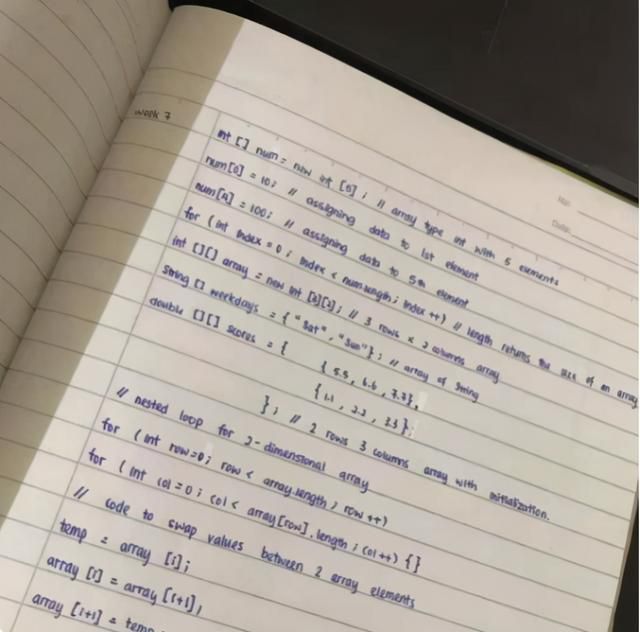
有种字体叫“蚂蚁体”,看起来乖巧娟秀,阅卷老师看见却很想扣分!
最近在网络上,有一种特别火的字体称之为蚂蚁体,为什么会叫这个名字呢?是因为这种字体的排版特别的工整,而且字体特别的小,就像是一群小蚂蚁在搬家一样,于是就称之为了蚂蚁体。虽然说,看起来排版非常的工整,而且很干净,但是字体太过于小了,不够大气,可能在查看的时候并不方便查看。
而且太过于限制了,很死板,没有一点点自由发挥的空间。这种蚂蚁体,将汉字的特点都给磨平了,在一个空间。非常的小巧,没有一点其他的特色。而且老师在查看这种字体的学生的时候,会觉得非常的困难,因为太过于小巧,甚至还有可能会导致看不清的情况出现。
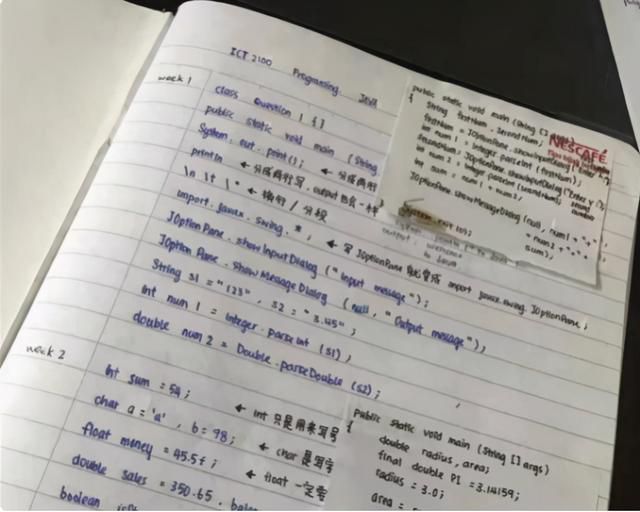
因此,老师也不喜欢用这种字体来写字,甚至有可能会因为用这种字体来写字,而导致自己丢了一些分数。现在大多数的考试都会进行电脑阅卷,将试卷进行扫描,老师就在电脑上面看大家的试卷。如果要是试卷的字体写得特别的不工整。
或者是不好看的话,就有可能会导致老师们感觉到非常的厌烦,或者是看不进去这些答案,就有可能会给同学进行一定的扣分。因为老师每天所需要查看的试卷量都特别的大,而且长时间地盯着电脑也会产生是觉得疲劳。
如果字体还写得不够工整的话,就有可能会导致老师觉得特别的厌烦。特别是语文的主观题,字很多,看得老师肯定会觉得头非常的疼,字体不好看可能会给同学进行一定的扣分。
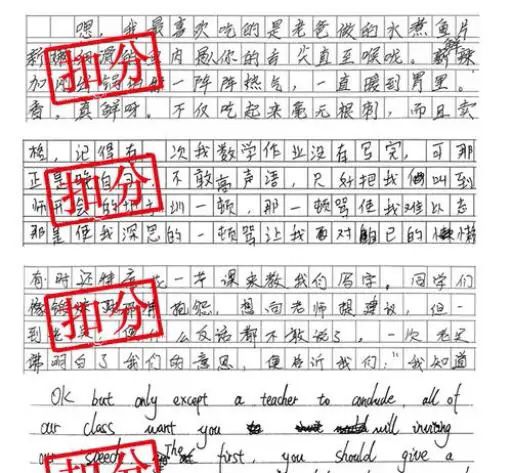
那么哪些字体适合学生使用?
1、标准楷体楷体
是书写中非常实用的一种字体,现在大多数的学生也都是练习这种字体。不仅工整,而且漂亮,又不太限制字体,大小也刚刚好。因此建议同学们都去练习这种字体。
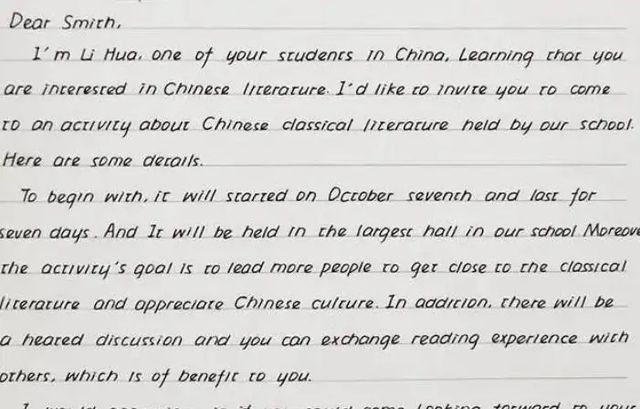
2、简单黑体
简单黑体,可以说得上是实用性最强的一种字体了。特别是老师进行考试,阅卷的时候,已经产生了疲劳。但是如果看到了这种字体的话很有可能就会减轻一定的疲劳,而且会看得比较清楚,因此推荐学生们可以使用这种字体来进行作答。
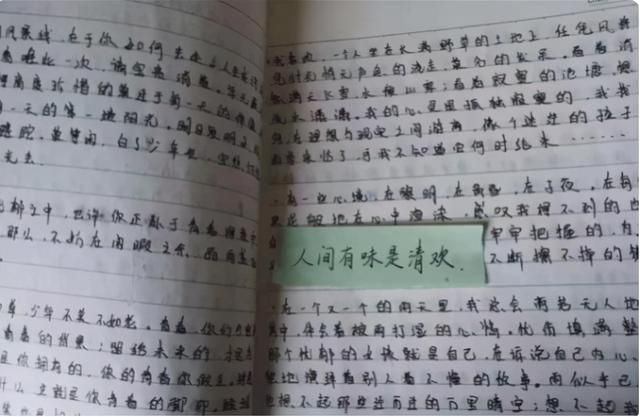
总结:
同学们在写字的时候,一定要工整地去书写自己的字体,稍有不慎的话就有可能会导致自己丢失掉一些分数,那样就是得不偿失了。毕竟在中国考试的分数还是作用非常大的,丢失一分,很有可能就会导致自己的排名落后很多。
作为父母的话一定要及时的去关注孩子的字体,一定要将孩子的字体纠正过来,不要让孩子写的字体特别的丑,对于孩子以后的发展也不是很好。